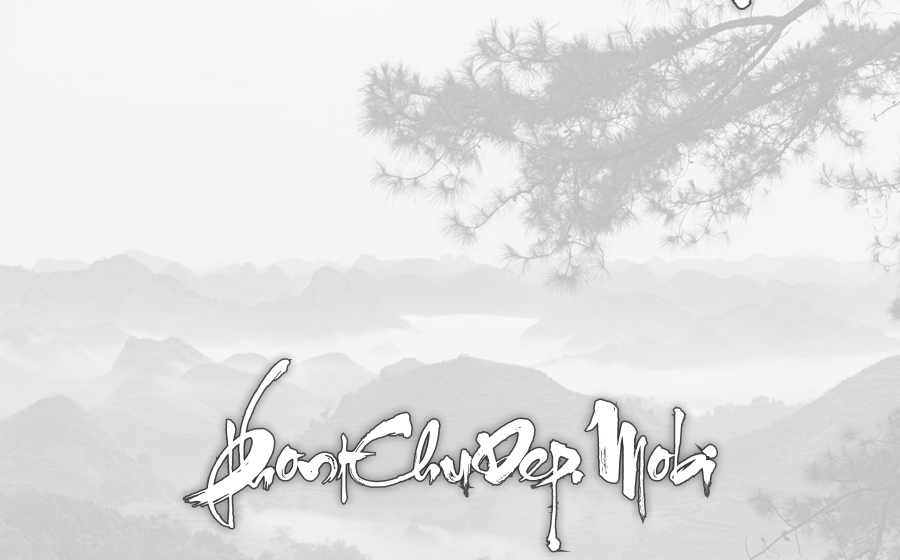
Font UTM Thư Pháp Thiên Ân Việt Hóa
UTM Thu Phap Thien An
UTM Thư Pháp Thiên Ân là một font chữ thư pháp đầy nghệ thuật và sự tinh tế, được sáng tạo bởi Đinh Kiên. Sự kỳ công trong thiết kế của font này thể hiện rõ nét qua việc sử dụng các ký tự thư pháp do thư pháp gia Đăng Học phát triển. Với những đường nét uyển chuyển và tinh xảo, UTM Thư Pháp Thiên Ân tái hiện một cách sống động phong cách thư pháp truyền thống, gợi nhớ đến nghệ thuật của các ông đồ xưa. Đặc biệt, việc đặt tên “Thiên Ân” là một món quà ý nghĩa từ tác giả dành cho con trai nhân dịp sinh nhật, khiến cho font chữ này càng thêm sâu sắc và đầy cảm xúc.
Với sự việt hóa tỉ mỉ bởi Thiên Minh, font này cung cấp đầy đủ các dấu và ký tự tiếng Việt, đảm bảo một trải nghiệm sử dụng hoàn hảo. Không chỉ dừng lại ở đó, UTM Thư Pháp Thiên Ân còn hỗ trợ nhiều ngôn ngữ khác, nhờ đó nó có thể áp dụng rộng rãi trong những thiết kế mang tầm quốc tế. Nếu bạn là thành viên của cộng đồng sáng tạo trên FontChuDep.mobi, chắc chắn bạn đã biết đến font chữ này khi nó được sưu tầm và giới thiệu đến với người dùng, đem lại thêm sự lựa chọn phong phú cho các dự án thiết kế. Với đặc điểm đường nét mềm mại và phong cách thư pháp độc đáo, đây là lựa chọn lý tưởng cho các thiết kế như thiệp mời, tiêu đề, poster và những dự án đòi hỏi sự tinh tế và nghệ thuật.